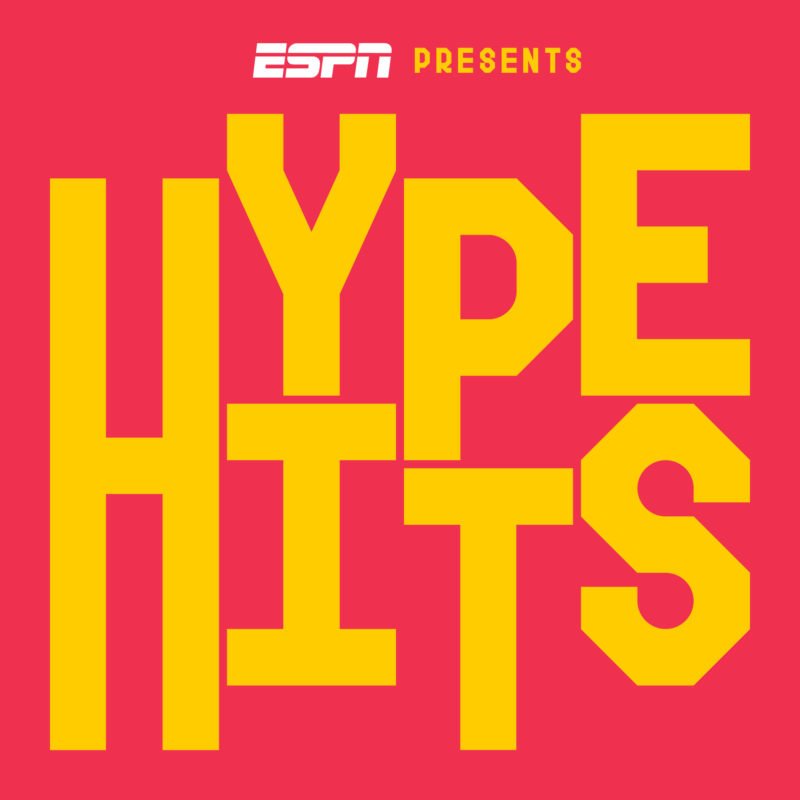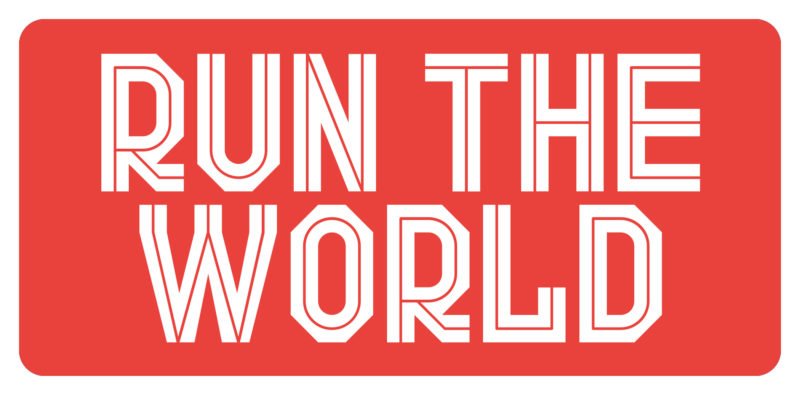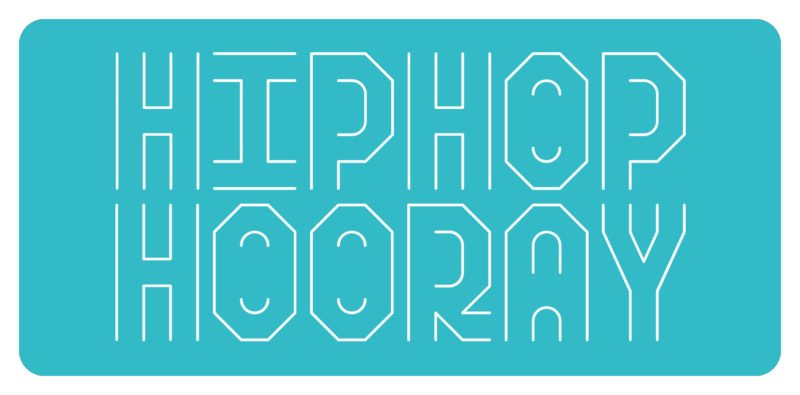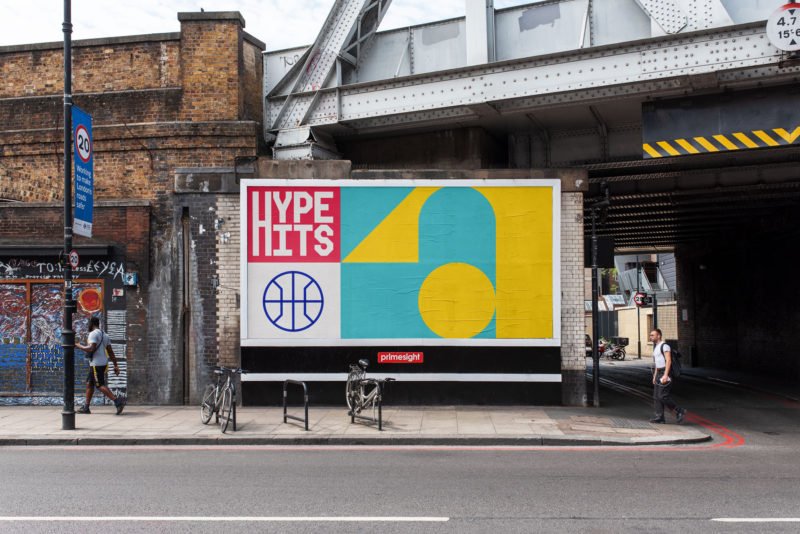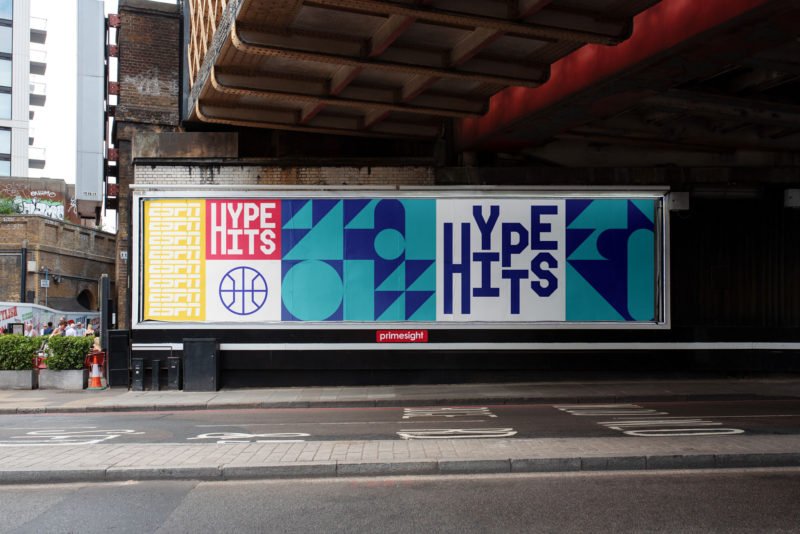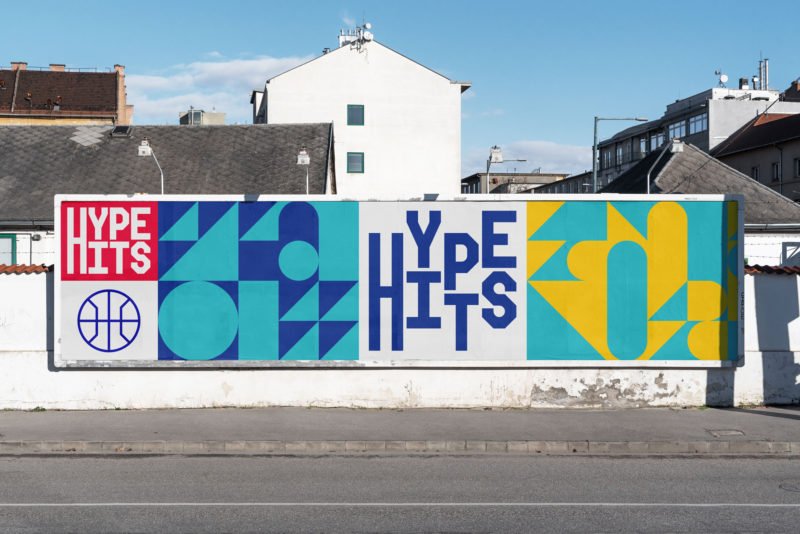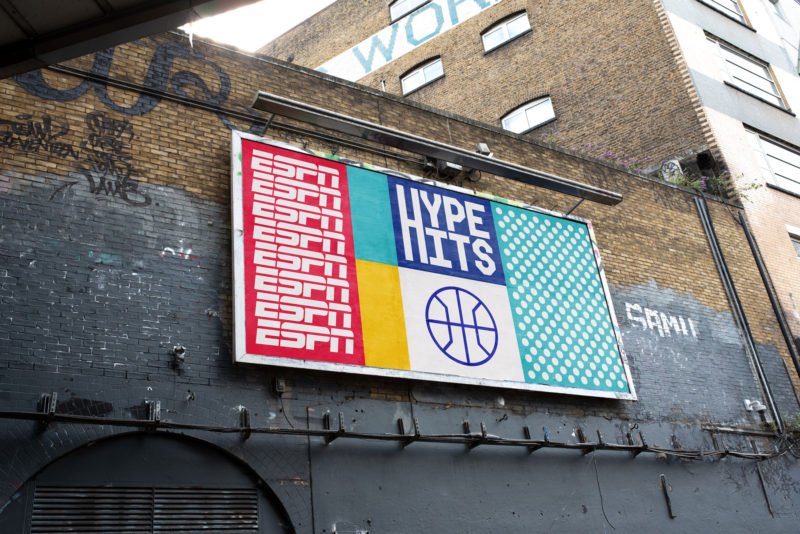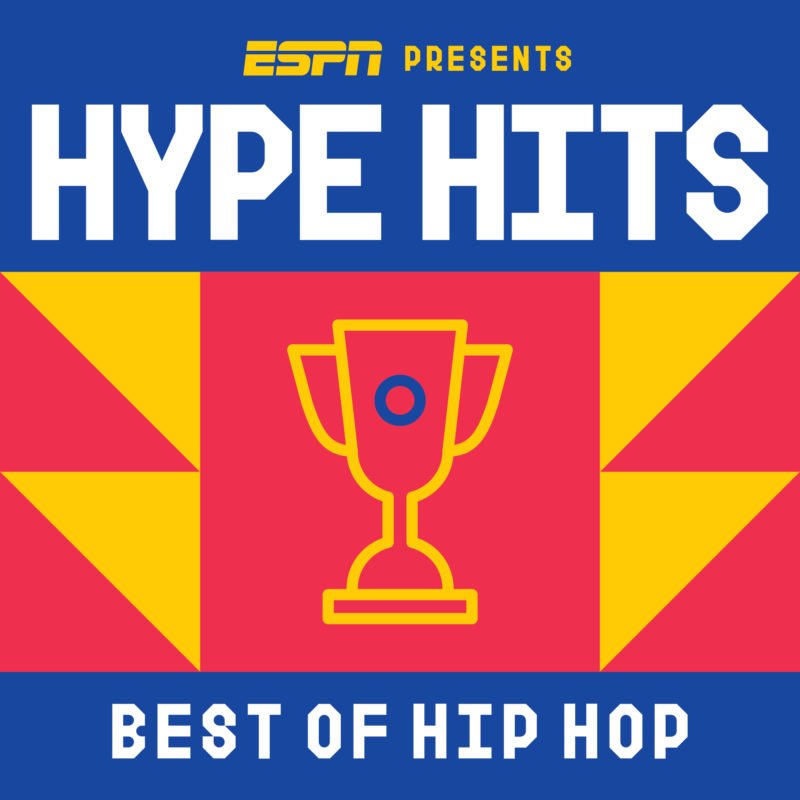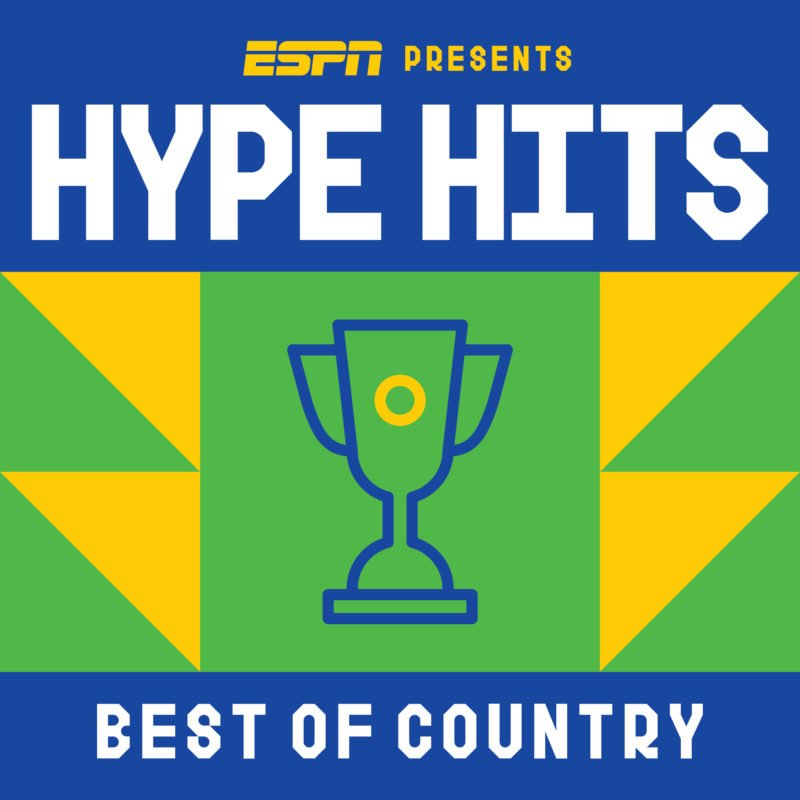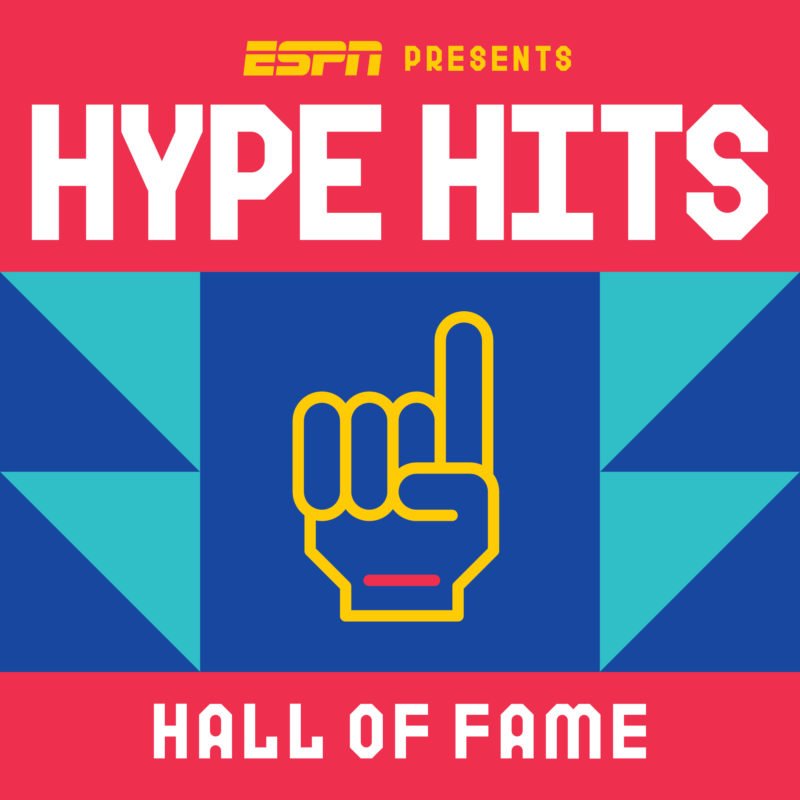
TwoPoints.Net desarrolla la tipografía de Hype Hits, el sello musical de ESPN
Personalidad, versatilidad y eficiencia,… nada más, nada menos
TwoPoints.Net, el estudio fundado en 2007 por Martin Lorenz y Lupi Asensio, ha sido el encargado desarrollar la tipografía Hype Hits, la marca a través de la cual ESPN, el gigante de la retransmisión deportiva estadounidense, aglutina las canciones más icónicas y/o representativas de la historia del deporte. «Son los temas que suenan en los estadios, vestuarios, autobuses y auriculares, y prepara a los atletas y fanáticos para cada competencia», comenta Lorenz.
El trabajo de TwoPoints, que opera actualmente desde Hamburgo, Berlín y Barcelona, consistía en desarrollar el sistema tipográfico completo del proyecto (dos fuentes —en tres estilos—, patrones, pictogramas y plantillas). El equipo creativo de ESPN seria el encargado realizar las composiciones a partir de este set. Por esta razón, la propuesta TwoPoints no solo tenía que tener la personalidad para estar a la altura de una iniciativa de este calado, también ser lo suficientemente versátil para adaptarse al sinfín de formatos y soportes que existen actualmente. Sin duda, un trabajo al alcance de pocos.
Con estos antecedentes y utilizando la primera andadura de ESPN en la música, un álbum recopilatorio editado hace exactamente 25 años titulado Jock Jams, Lorenz, Asensio y compañía, completaron un trabajo inapeable.
Aunque se podría llegar a decir que existen puntos en común, conexiones o ciertos rasgos reconocibles propios de su estilo, la gente de TwoPoints se las arregló para ofrecernos un proyecto nuevo e inspirador, tanto desde conceptual y artístico, como desde lo técnico. Simplemente brutal. «Como siempre, trabajar con ESPN ha sido muy divertido. No podríamos estar más felices».